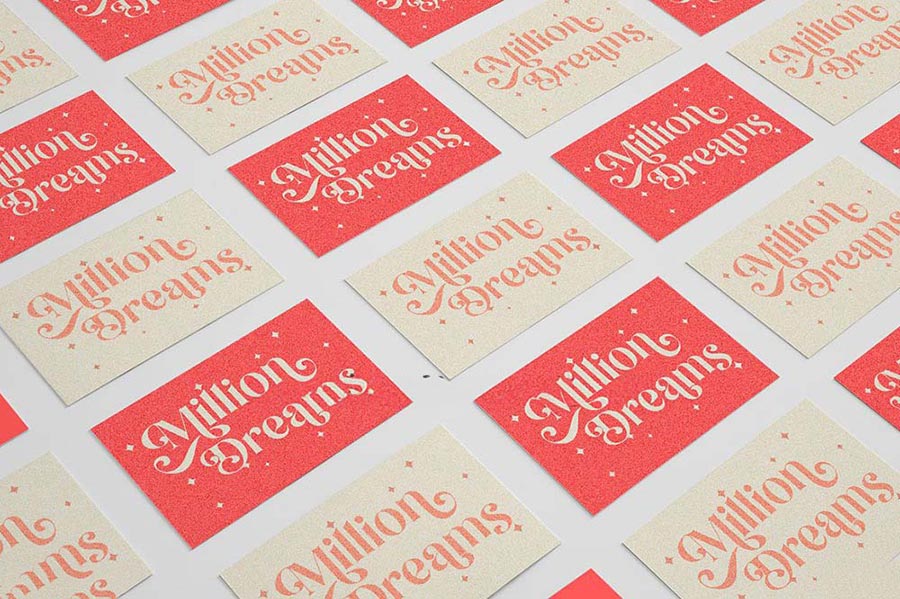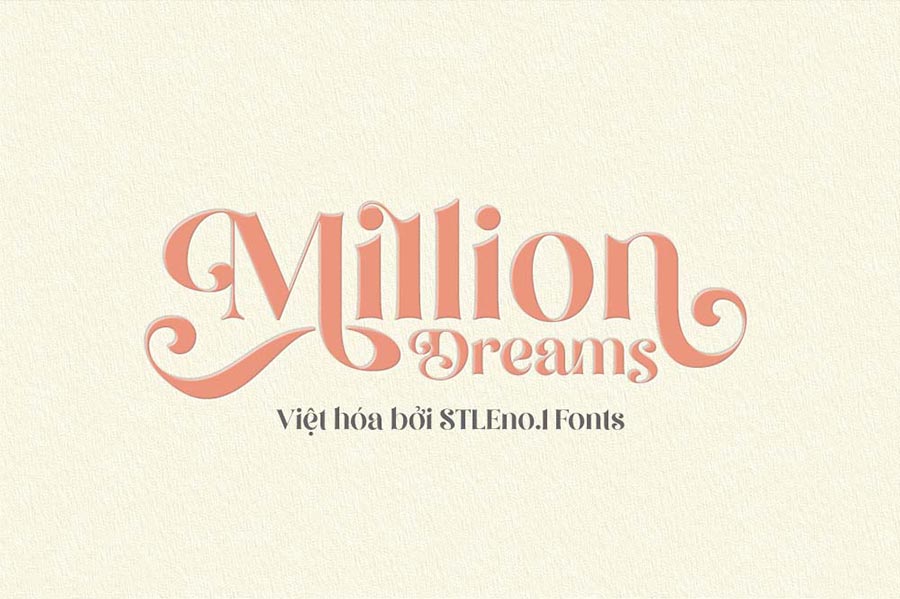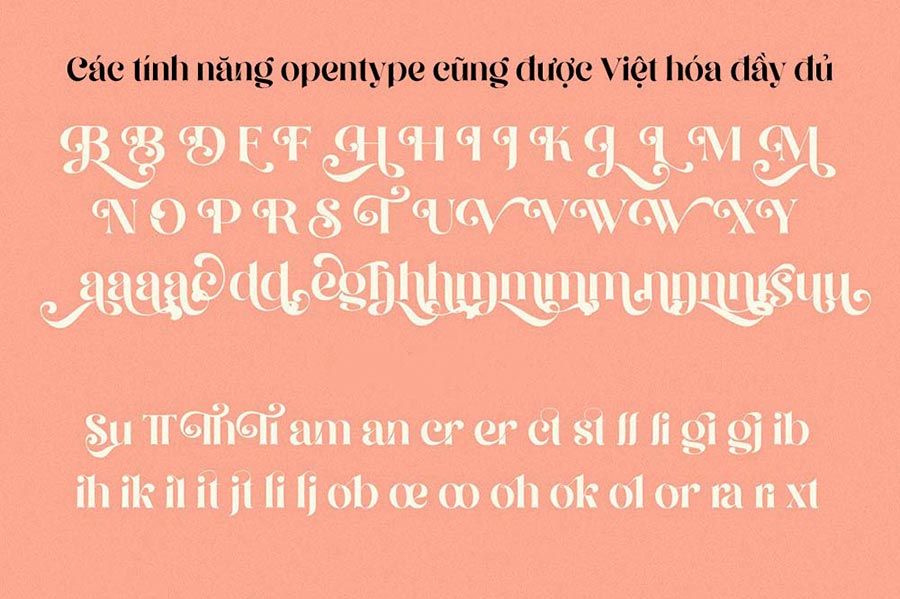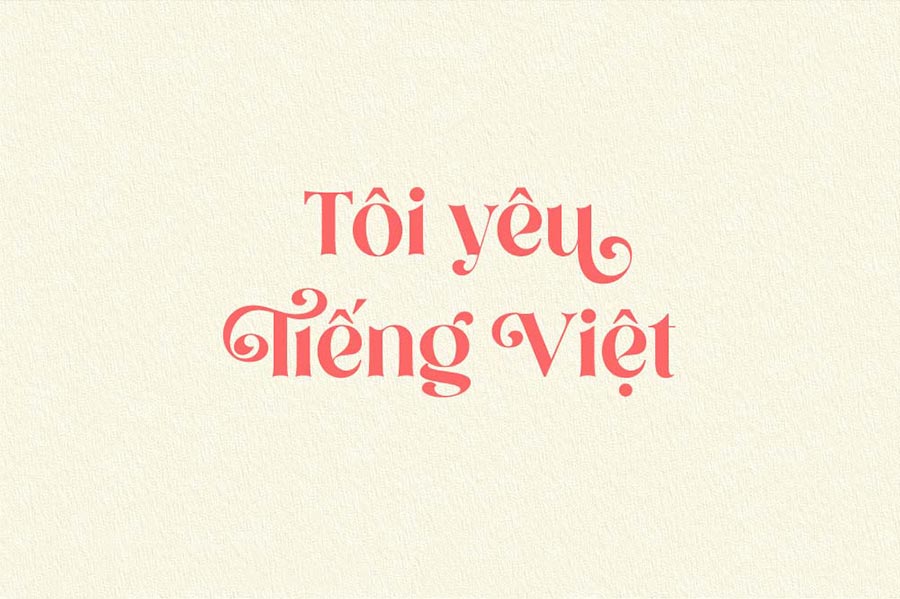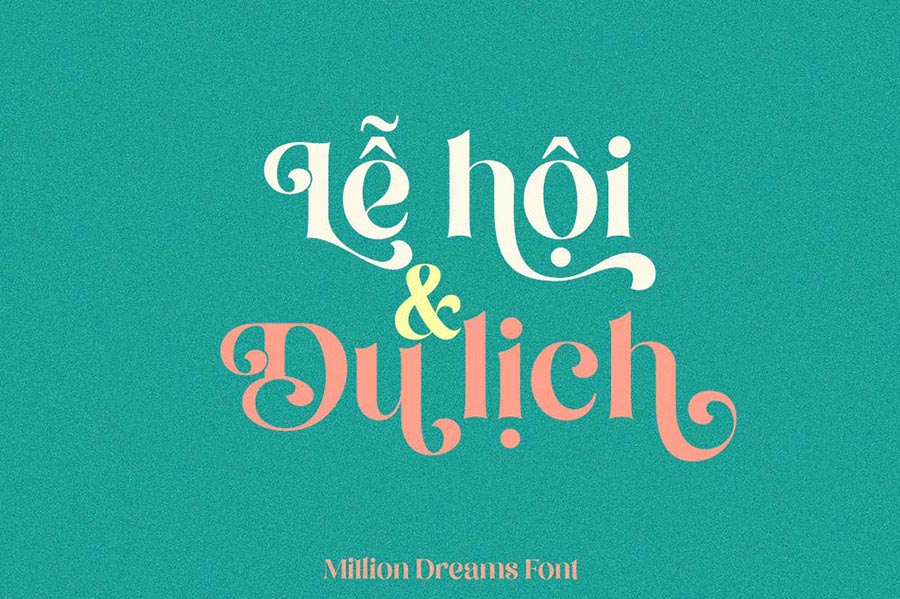
Chia Sẻ Miễn Phí Font Việt Hóa SVN- Million Dreams Phong Cách Vui Tươi, Nữ Tính
Font chữ đóng vai trò quan trọng trong việc truyền tải thông điệp và tạo dựng hình ảnh cho các sản phẩm thiết kế. Trong bối cảnh hiện nay, nhu cầu sử dụng font chữ Việt hóa ngày càng gia tăng, đặc biệt là những font mang phong cách độc đáo và phù hợp với thị hiếu người dùng. Một trong những lựa chọn nổi bật là font SVN- Million Dreams, được sadesign.vn chia sẻ miễn phí, mang lại phong cách vui tươi và nữ tính.
SVN- Million Dreams là một font chữ được thiết kế với sự tinh tế và sáng tạo, giúp các nhà thiết kế dễ dàng thể hiện ý tưởng của mình một cách sinh động và thu hút. Với đặc điểm nổi bật là sự kết hợp hài hòa giữa các đường nét mềm mại và phong cách hiện đại, font chữ này hứa hẹn sẽ là lựa chọn lý tưởng cho các sản phẩm thiết kế hướng tới đối tượng nữ giới hoặc các dự án cần sự tươi mới và sáng tạo.
Một trong những ưu điểm của SVN- Million Dreams chính là khả năng ứng dụng đa dạng. Font chữ này có thể được sử dụng trong nhiều lĩnh vực khác nhau như thiết kế bao bì, quảng cáo, truyền thông xã hội, và thậm chí cả trong các dự án nghệ thuật. Điều này giúp các nhà thiết kế tiết kiệm thời gian và công sức trong việc tìm kiếm một font chữ phù hợp, đồng thời đảm bảo tính thẩm mỹ và chuyên nghiệp cho sản phẩm cuối cùng.